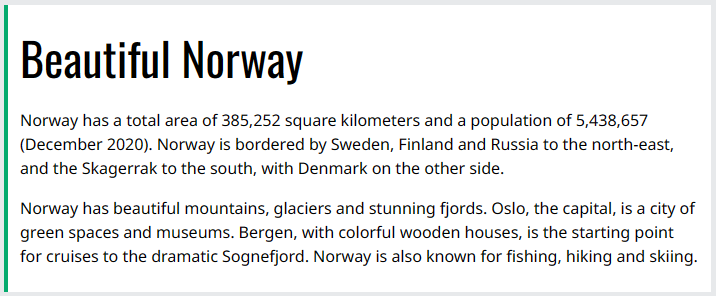
CSS 很棒的字体搭配
出色的字体搭配对于出色的设计至关重要。
字体配对规则
以下是创建出色字体配对的一些基本规则:
1. 补充
找到相互补充的字体配对总是安全的。
一个好的字体组合应该协调一致,不要太相似或太不同。
2.使用字体超家族
字体超系列是一组旨在协同工作的字体。因此,在同一超家族中使用不同的字体是安全的。
例如,Lucida 超系列包含以下字体: Lucida Sans、Lucida Serif、Lucida Typewriter Sans、Lucida Typewriter Serif 和 Lucida Math。
3. 对比
过于相似的两种字体经常会发生冲突。然而,对比,完成 正确的方式,在每种字体中发挥出最佳效果。
示例:将衬线与无衬线组合是众所周知的组合。
一个强大的超家族包括相同字体的衬线和无衬线变体(例如 Lucida 和 Lucida Sans)。
4.只选择一个
选择一种字体建立层次结构,可以通过改变尺寸、重量和颜色来实现。
1 | 毫无疑问,“Verdana, sans-serif”是第一选择: |
Georgia 和 Verdana
Georgia 和 Verdana 是一个经典的组合。它还坚持 Web 安全字体标准:
1 | Use the "Georgia" font for headings, and "Verdana" for text: |
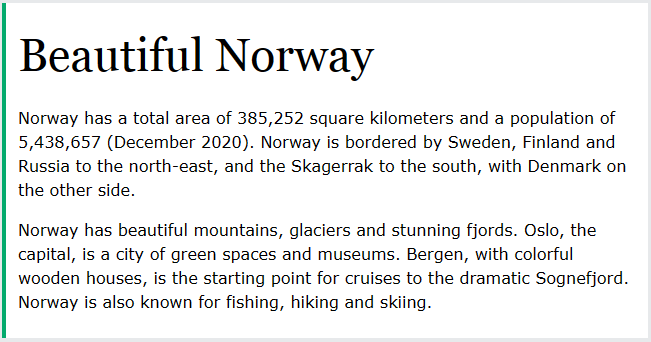
Helvetica 和 Garamond
Helvetica 和 Garamond 是另一种使用 Web 安全字体的经典组合:
1 | 标题使用“Helvetica”字体,文本使用“Garamond”字体: |
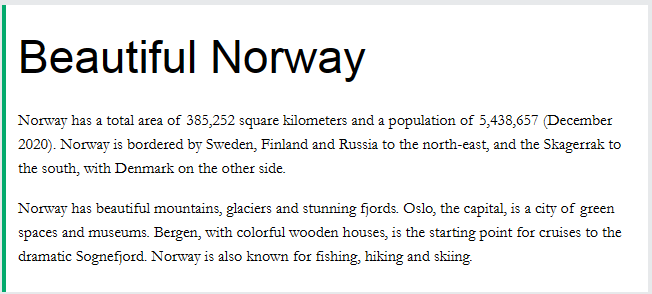
热门 Google 字体配对
如果您不想在 HTML 中使用标准字体,则可以使用 Google 字体。
Google Fonts 是免费使用的,并且有 1000 多种字体可供选择。
以下是一些流行的 Google Web 字体配对。
Merriweather 和 Open Sans
1 | 标题使用“Merriweather”字体,文本使用“Open Sans”字体: |
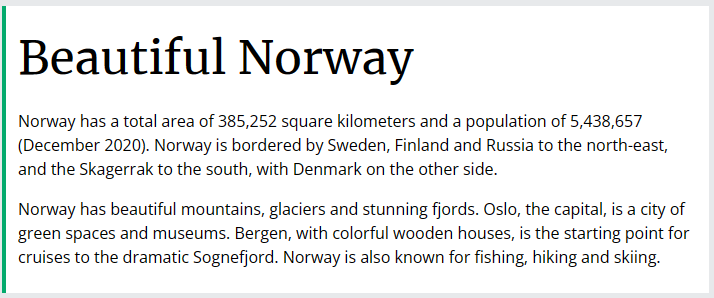
Ubuntu 和 Lora
1 | 标题使用“Ubuntu”字体,文本使用“Lora”字体: |
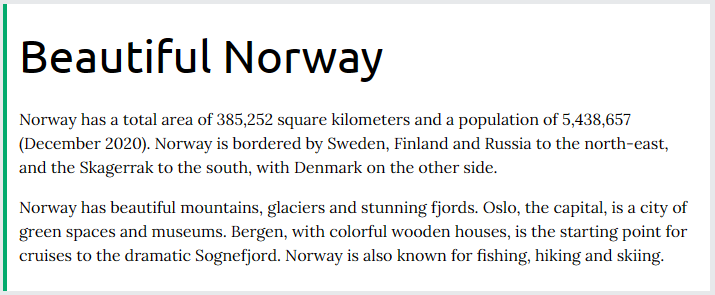
Abril Fatface 和 Poppins
1 | 标题使用“Abril Fatface”字体,文本使用“Poppins”字体: |
Cinzel and Fauna One
1 | 标题使用“Cinzel”字体,文本使用“Fauna One”字体: |
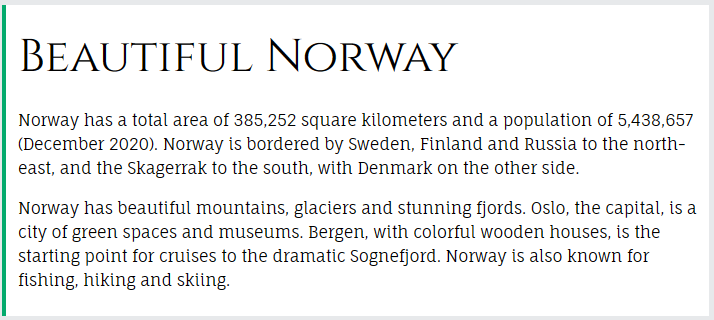
Fjalla One 和 Libre Baskerville
1 | 标题使用“Fjalla One”字体,文本使用“Libre Baskerville”字体: |
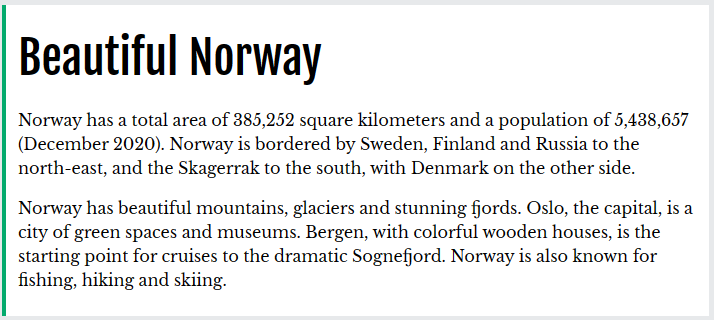
Space Mono 和 Muli
1 | 标题使用“Space Mono”字体,文本使用“Muli”字体: |
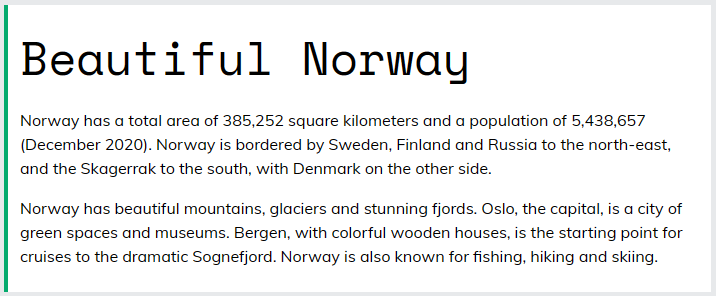
Spectral和Rubik
1 | 标题使用“Spectral”字体,文本使用“Rubik”字体: |
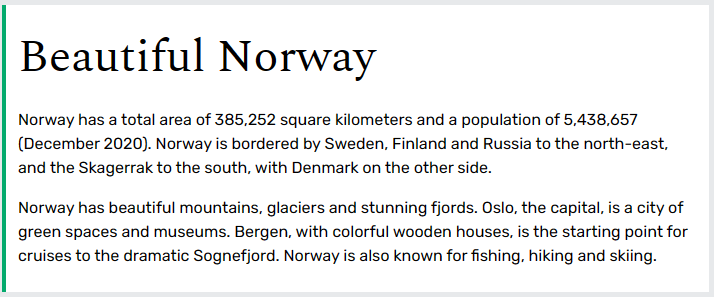
Oswald和Noto Sans
1 | 标题使用“Oswald”字体,文本使用“Noto Sans”字体: |